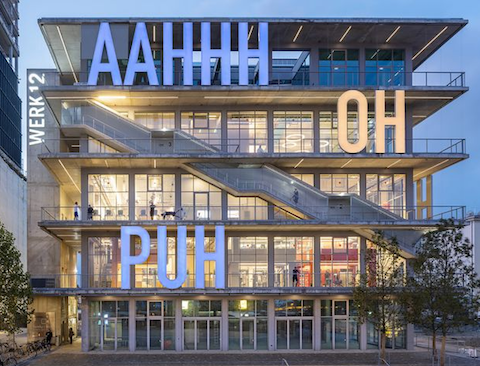
Ah, oh, uh.
(… ich find's strunzlangweilig, aber vielleicht reißen es die paar Buchstaben ja raus.)
Wie muss erst der Rest aussehen, wenn das das beste war. :-|
Es geht bei dem Haus wohl mehr um die inneren Werte. Der Kritiker der Süddeutschen Zeitung schreibt dazu unter anderem: »Denn der Bau, es ist eine nach außen hin fast schon typische MVRDV-Hochstapelei, ist klug konzipiert als Hybrid, der auf raffinierte Weise Mischnutzungen aller Art möglich macht. ImMoment sind es Büros, Fitness, Gastronomie – aber die Flexibilität der Grundrisse lässt vieles zu. Das Haus ist ein modern ornamentierter Bau der Möglichkeiten, der am richtigen Ort lautstark ist. Es geht ja um ein Industrieareal. Außerdem ist das Haus eine Antwort auf den Mangel an stadträumlicher Flexibilität.«
Man kann sich vieles schönreden … das Haus mag sicherlich klug durchdacht und flexibel in der Nutzung sein, die Optik vermittelt aber bestenfalls das Gefühl einer Hochgarage aus den 80er Jahren. Da reißen es die Comicwörter auch nicht raus. Wenn schon der Mensch vom Haus nicht angesprochen wird, wenn nichts Einladendes zu sehen ist, nur toter grauer Beton, eine Halle für Maschinen, nicht für Menschen, wie kann das das "beste Bauwerk des Jahres" sein? Soll ein Gebäude nicht dem Menschen dienen?
Da reißen es die Comicwörter auch nicht raus.
Die finde ich ja fast noch schlimmer, weil wirklich nur aufgesetzt, als das Haus an sich.
Über Architektur läßt sich genauso wie über Typografie immer kontrovers diskutieren. Ach wenn mir der Baustil auch nicht zusagt muss ich jedoch sagen, das dieses Gebäude doch dem Menschen dient. Es ist ja kein "Lost Place". Es wirkt eher so als würde da demnächst noch die Glasfassade kommen.  Es erinnert mich ein wenig an "Cube" am Berliner Hauptbahnhof . Der in einer Bauphase so aussah wie im 2. Bild , da hatte ich schon befürchtet, dass das Gebäude so bleibt wie im oberen Teil. Mit Glasfassade und dem richtigen Licht ist das sogar sehenswert. wie hier https://deaneau.wixsite.com/page/cube-berlin . Habe ich das richtig gelesen dass die Versalien 5 Meter hoch sind? Das bedeutet ja, dass jede Etage eine Raumhöhe von 5 Metern hat. Die Heizkosten will ich aber nicht zahlen wollen. Mich würde da eher die Frage umtreiben wie gut die Ökobilanz ist. Mir schein dass Architekten im 20. und 21. sehr ähnliche Architektur schaffen, die man beliebig in jede Stadt setzen kann und keiner könnte sagen ist das jetzt München, Hamburg oder Berlin. Schöne Architektur ist das hier in meinen Augen.
Über Architektur läßt sich genauso wie über Typografie immer kontrovers diskutieren. Ach wenn mir der Baustil auch nicht zusagt muss ich jedoch sagen, das dieses Gebäude doch dem Menschen dient. Es ist ja kein "Lost Place". Es wirkt eher so als würde da demnächst noch die Glasfassade kommen.  Es erinnert mich ein wenig an "Cube" am Berliner Hauptbahnhof . Der in einer Bauphase so aussah wie im 2. Bild , da hatte ich schon befürchtet, dass das Gebäude so bleibt wie im oberen Teil. Mit Glasfassade und dem richtigen Licht ist das sogar sehenswert. wie hier https://deaneau.wixsite.com/page/cube-berlin . Habe ich das richtig gelesen dass die Versalien 5 Meter hoch sind? Das bedeutet ja, dass jede Etage eine Raumhöhe von 5 Metern hat. Die Heizkosten will ich aber nicht zahlen wollen. Mich würde da eher die Frage umtreiben wie gut die Ökobilanz ist. Mir schein dass Architekten im 20. und 21. sehr ähnliche Architektur schaffen, die man beliebig in jede Stadt setzen kann und keiner könnte sagen ist das jetzt München, Hamburg oder Berlin. Schöne Architektur ist das hier in meinen Augen. Dusseldorf-Zoo-Achenbach43-Fassade-re.jp
..schöne Architektur...          Es recht zu machen Jedermann, ist eine Kunst, die niemand kann.   -- Gut daß Geschmack nicht genormt ist!
Für mich ist das Bauhauskitsch – ich kenne hier in Berlin einige ganz ähnliche Fabrik– und Industriegebäude aus den 1920ern (die stehen teilweise unter Denkmalschutz). Warum man das jetzt 100 Jahre später bauen muss, erschließt sich mir nicht. Ebensowenig, wie die Sache mit dem Stadtschloss oder dem Herrn Jauch seine Garnisonskirche …
Die Architektur möchte ich ohne weitere Bilder vom Innenraum bzw. ohne Grundrisse nicht beurteilen – so eine Haus besteht ja nicht nur aus einer Ansicht Die »Typografie« auf der Fassade finde ich aber sowohl inhaltlich als auch formal schlicht langweilig. Das hier Comic- und Grafittikultur zitiert wird kann ich der Umsetzung nur schwer entnehmen.
Für mich ist das Bauhauskitsch –
Du meinst mit Sicherheit nicht das Architektur Projekt in Düsseldorf.
Die Architektur möchte ich ohne weitere Bilder vom Innenraum bzw. ohne Grundrisse nicht beurteilen –
nicht das Architektur Projekt in Düsseldorf
Nein, das meine ich nicht (ohnehin hat der Link  bei mir irgendwie nicht funktioniert). Ich war immer noch beim Werk 12 …
Für die einen ein Traditionsbruch, für die anderen ein gesellschaftlicher Fortschritt in Affinity:image.png.087ff9cd868ac91beb2b1b71199d5fa3.png
Es juckt mich sehr, mal was kyrillisches zu machen. Leider besteht da so gut wie keine Nachfrage.
Naja, bei denen die typischerweise nur lateinische Fonts machen freilich nicht. Aber der kyrillische Markt ist trotzdem groß und voller Leben.
Aber der kyrillische Markt ist trotzdem groß und voller Leben.
In Europa kann ich mir das gut vorstellen. Hätte ich ausreichend europäische Kunden, würde ich das gerne mal versuchen. Aber 99% meiner Kundschaft ist in den USA. Meine Versuche, auch in Europa Werbung zu machen, ziehen aus irgendeinem Grund nicht. Vielleicht funkt meine Website da nicht richtig? Oder kommt Online-Werbung bei Euch nicht durch (google ads). Daß sie nur auf englisch zu haben ist, sollte doch zumindest in Deutschland kein Problem sein. Oder liege ich da falsch?
Na, zumindest bei der Suchmaschine Duckduckgo kannst Du eine Funktion anklicken, mit der Dir primär deutschsprachige Seiten angezeigt werden. In diesem Falle würdest Du mit einer rein englischen Seite durchs Raster fallen. Ist Deine Seite mehrsprachig angelegt?
Kathrin, könntest Du das mal probieren? Wenn Du bei Google und DuckDuckGo nach "Shakespeare font" suchst, sollte ich gleich das erste Resultat sein.
Ich bin zwar nicht Kathrin, war aber mal so frei, zu testen. Bei Google kommt Waldenfont (das bist du doch?) auf Platz 1 nach ein paar Bildern. Bei DuckDuckGo auf Platz 9, wenn die Sprachfilterung deaktiviert ist, und ebenso mit aktiviertem Filter für Deutsch.
Und das geht auch so ganz einfach ohne den entsprechenden kulturellen Hintergrund?
Кто сказал, что я не говорю по-русски?